「ニューダンガンロンパV3 みんなのコロシアイ新学期」に「ダイナフォント 古籍銀杏」が採用
株式会社スパイク・チュンソフトが発売したPlayStationR4、PlayStationRVitaゲーム「ニューダンガンロンパV3 みんなのコロシアイ新学期」に「ダイナフォント 古籍銀杏」が採用されている。
古籍銀杏 書体見本
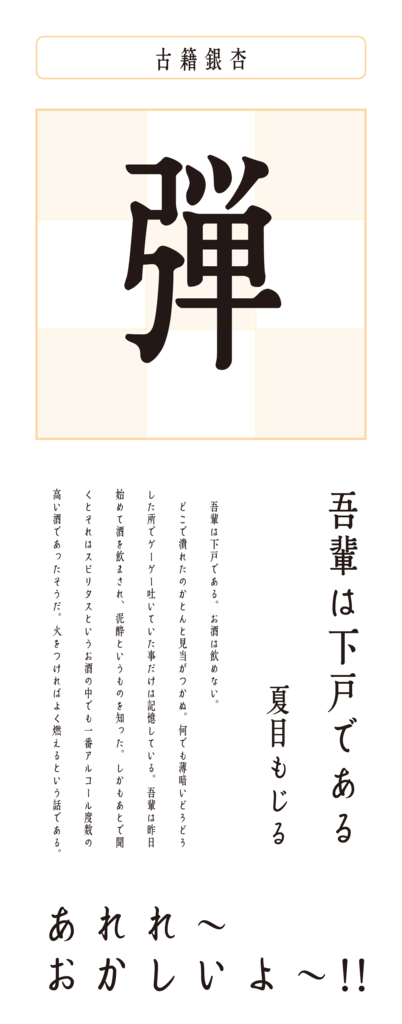
古籍銀杏
中国の古籍「天工開物」をモチーフとして開発された書体。「天工開物」の文字は、半円形となったストロークが繊細で、銀杏の葉っぱのような優雅さがある。古籍書体シリーズとしてグッドデザイン賞を受賞。
DynaFont古籍書体シリーズとは、台湾の「故宮博物院」に収録された古籍と復刻版の古籍の出版品から「元豊類稿」「唐百家詩選」「天工開物」「四庫全書」「范伯子集」の五冊に書かれた文字をベースに開発されたデジタル書体である。歴史的価値が高く文化性に優れた古籍文字に、長期の開発期間を費やしデザイン性を追求しブラッシュアップさせた事により、文化性と芸術性の高さが融合された稀有な書体として完成に至った。
「古籍木蘭」、「古籍真竹」、「古籍銀杏」、「古籍糸柳」、「古籍黒檀」の古籍の冠が名づけられた五つの書体は、それぞれに異なる特徴を有しながらも、どこか古風な情緒が醸し出されており、古籍書体シリーズとしての一体感を感じさせる書体として大きく評価され、2014年度グッドデザイン賞を受賞した。